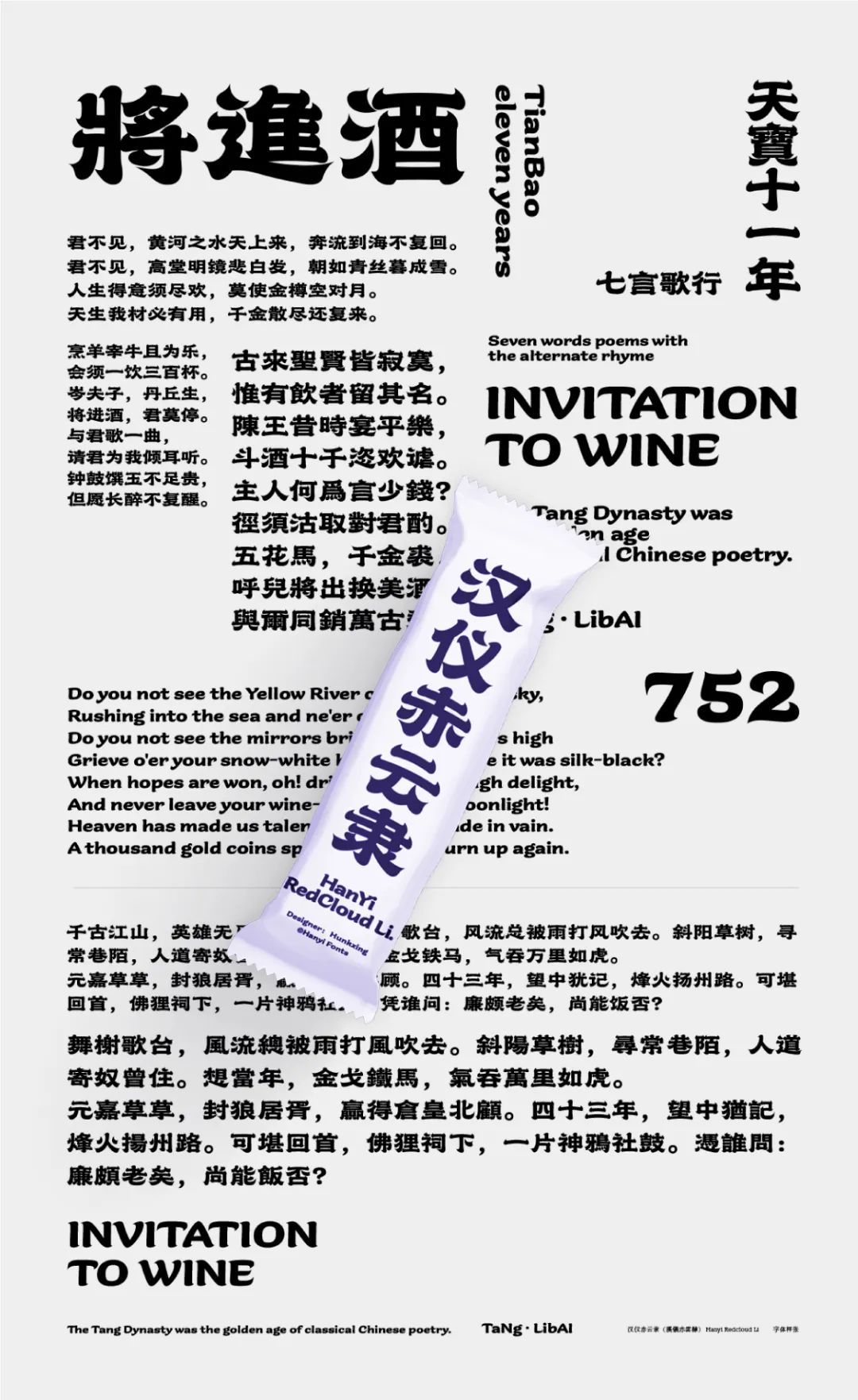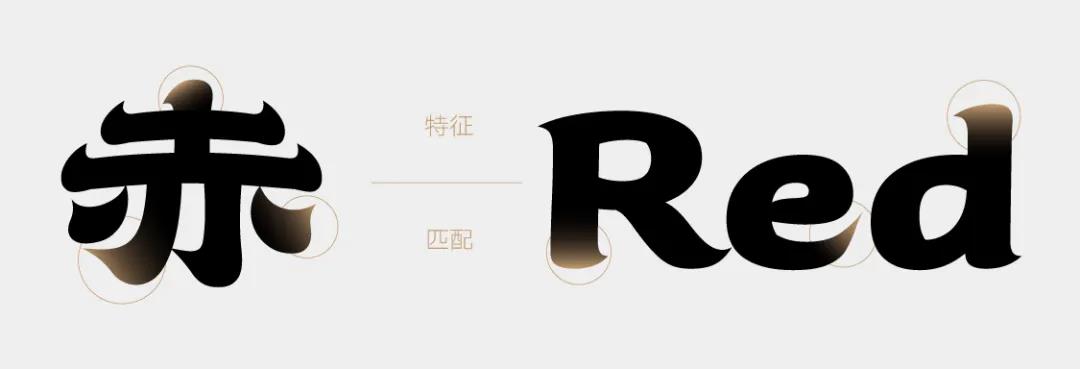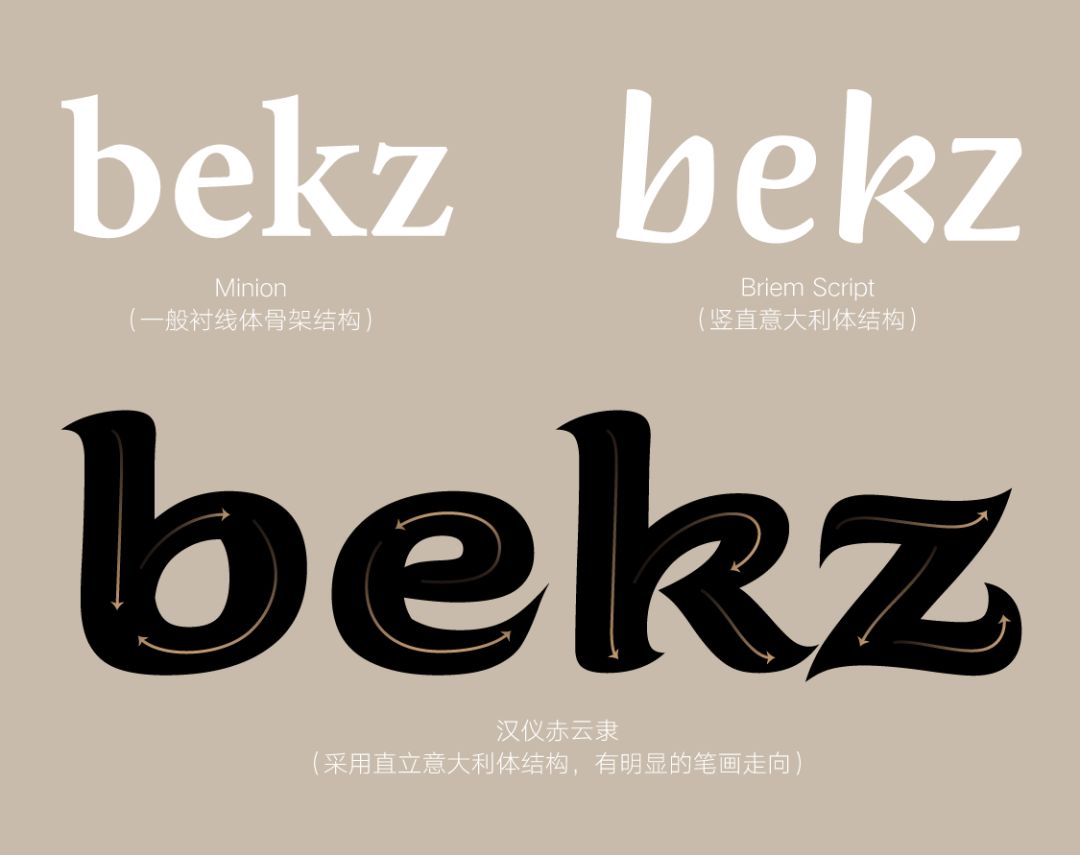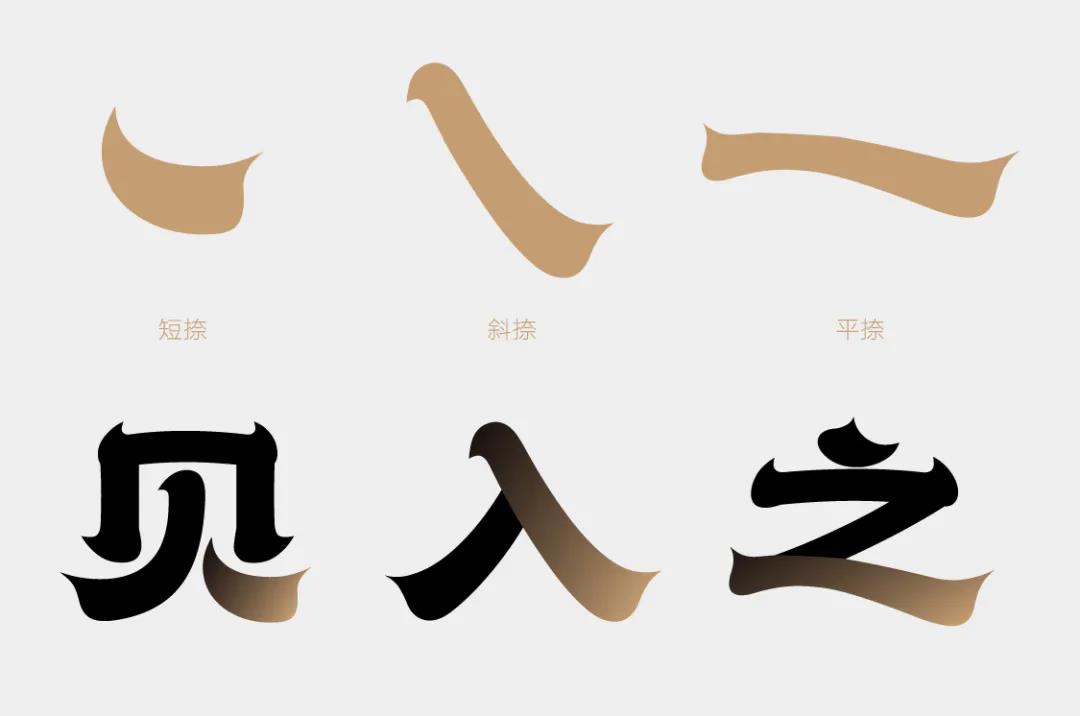
漢儀赤云隸W是由知名設(shè)計(jì)師行行珂與漢儀字庫(kù)合作打造的一款帶有隸書(shū)韻味的設(shè)計(jì)字體。這款字體運(yùn)用現(xiàn)代設(shè)計(jì)語(yǔ)言,在隸書(shū)的基礎(chǔ)上改造創(chuàng)新,給予了傳統(tǒng)字體新的生命力。漢儀赤云隸曾入選Award360°年度設(shè)計(jì)100、《第十四屆亞太設(shè)計(jì)年鑒》、《Design360°n.84#特刊#》和《字賦不凡2》。歡迎喜歡漢儀赤云隸W字體的朋友前來(lái)下載使用。
漢儀赤云隸,以隸書(shū)為原型進(jìn)行創(chuàng)作,字形略帶篆意,古中帶新。
漢儀赤云隸,采用了隸書(shū)的結(jié)構(gòu),字體寬扁,重心一致,字取橫勢(shì),給人一種穩(wěn)定、厚重的感覺(jué)。
漢儀赤云隸,在古隸書(shū)的基礎(chǔ)上融入張揚(yáng)外放的筆觸,在起筆、收筆處的筆畫(huà)設(shè)計(jì)上強(qiáng)化了筆鋒造型,具有一定裝飾性,如同燃燒的火苗一樣,在這個(gè)年輕的時(shí)代迸發(fā)出獨(dú)特的張力和韻味。
漢儀赤云隸,筆畫(huà)渾厚有力、氣勢(shì)宏大,行筆流暢有力度,線條飽滿(mǎn)有彈性,表現(xiàn)出了其生動(dòng)活潑的特點(diǎn)。
漢儀赤云隸的筆畫(huà)在不同的位置上有著不同的表達(dá)。以筆畫(huà)“捺”為例,按字形特點(diǎn)分為“短捺”、“斜捺”和“平捺”,“短捺”的捺身較短促;“斜捺”頭細(xì)尾粗,比較陡峭;“平捺”則一波三折,形似波浪。
漢儀赤云隸的西文有著明顯的筆畫(huà)走向。西文設(shè)計(jì)參照了傳統(tǒng)的英文書(shū)法,運(yùn)用Upright Italic(豎直意大利體)的骨架來(lái)對(duì)應(yīng)中文隸書(shū)這樣的書(shū)寫(xiě)感。